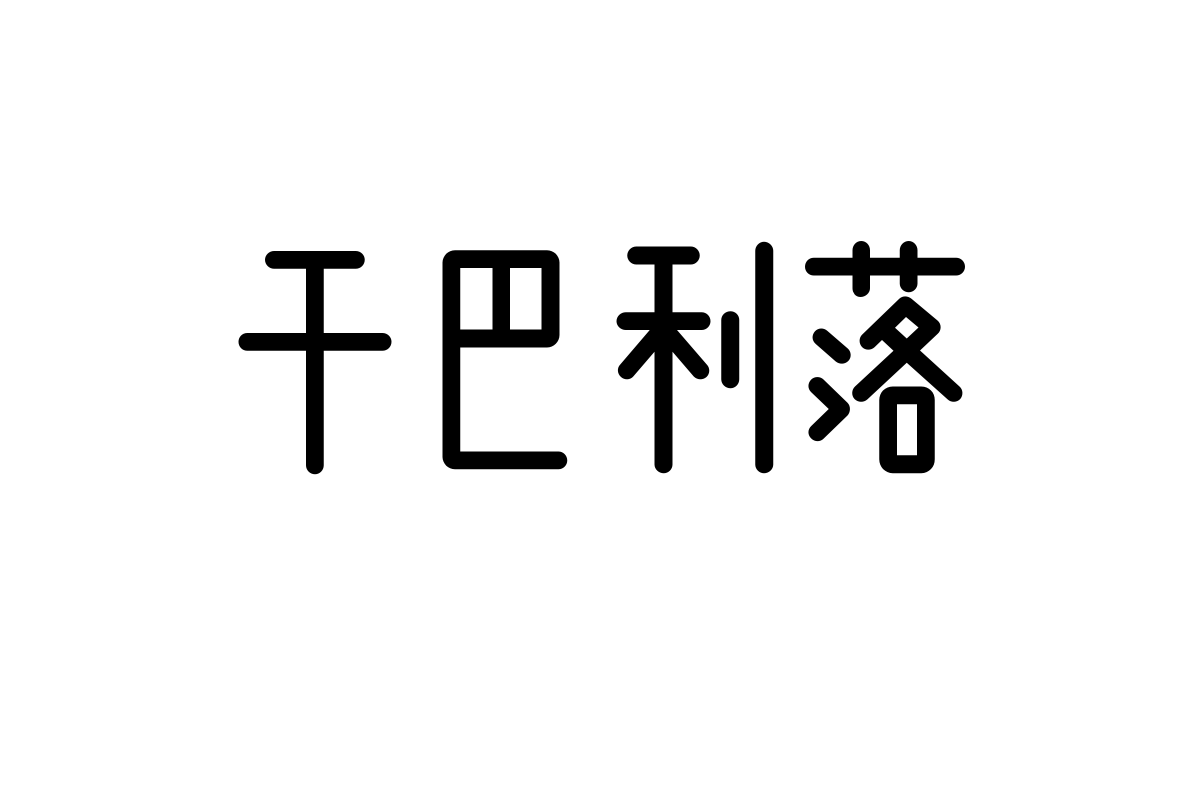
悟语体是一款现代中文字体,由造字工房设计。这款字体以其独特的风格和结构而闻名,具有强烈的个性和创意。它采用了简洁的线条和形状,以及大胆的色彩搭配,给人一种强烈的视觉冲击感。
悟语体的设计灵感来源于自然元素和抽象图形,如树木、花朵、山脉等。这些元素在字体中以不同的形式表现出来,使得整个字体充满了生机和活力。此外,悟语体的字形也具有一定的变化性,使得每个字符都呈现出独特的美感。
悟语体的应用场景非常广泛,无论是用于广告宣传、品牌标识、海报设计还是网页布局,都能展现出其独特的魅力。它的使用可以有效地提升设计作品的视觉效果和吸引力,使信息传递更加生动有力。
造字工房悟语体